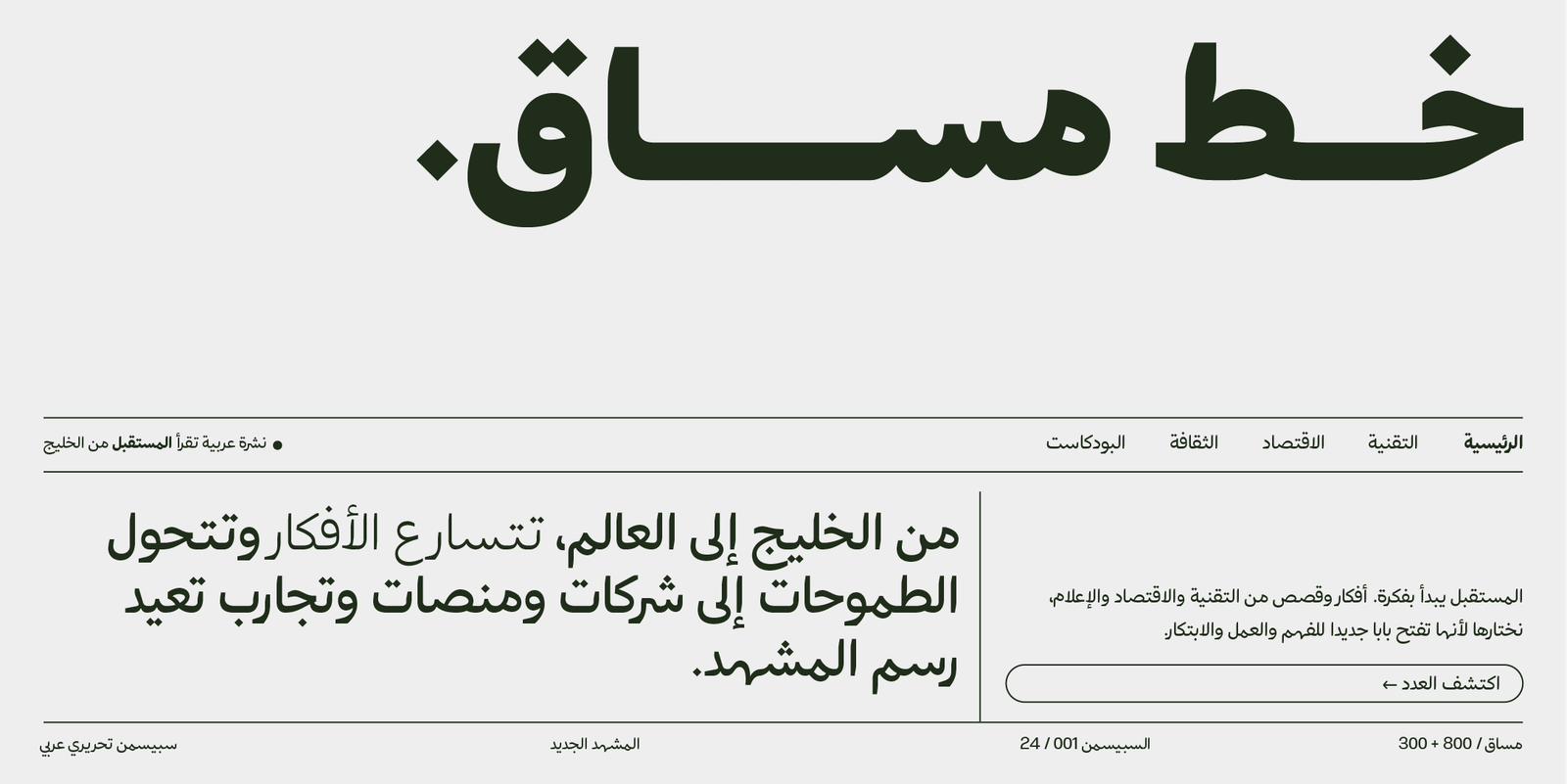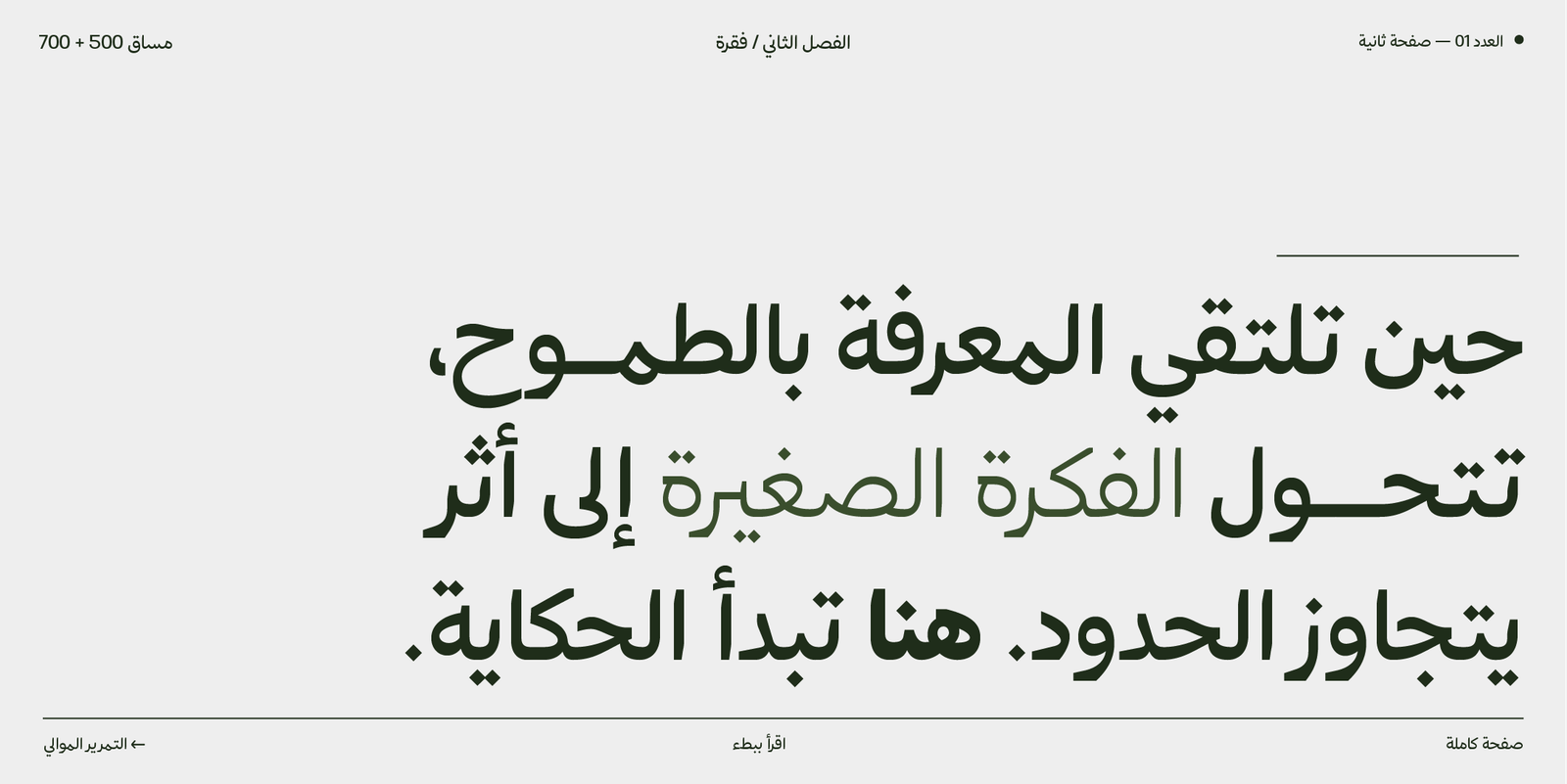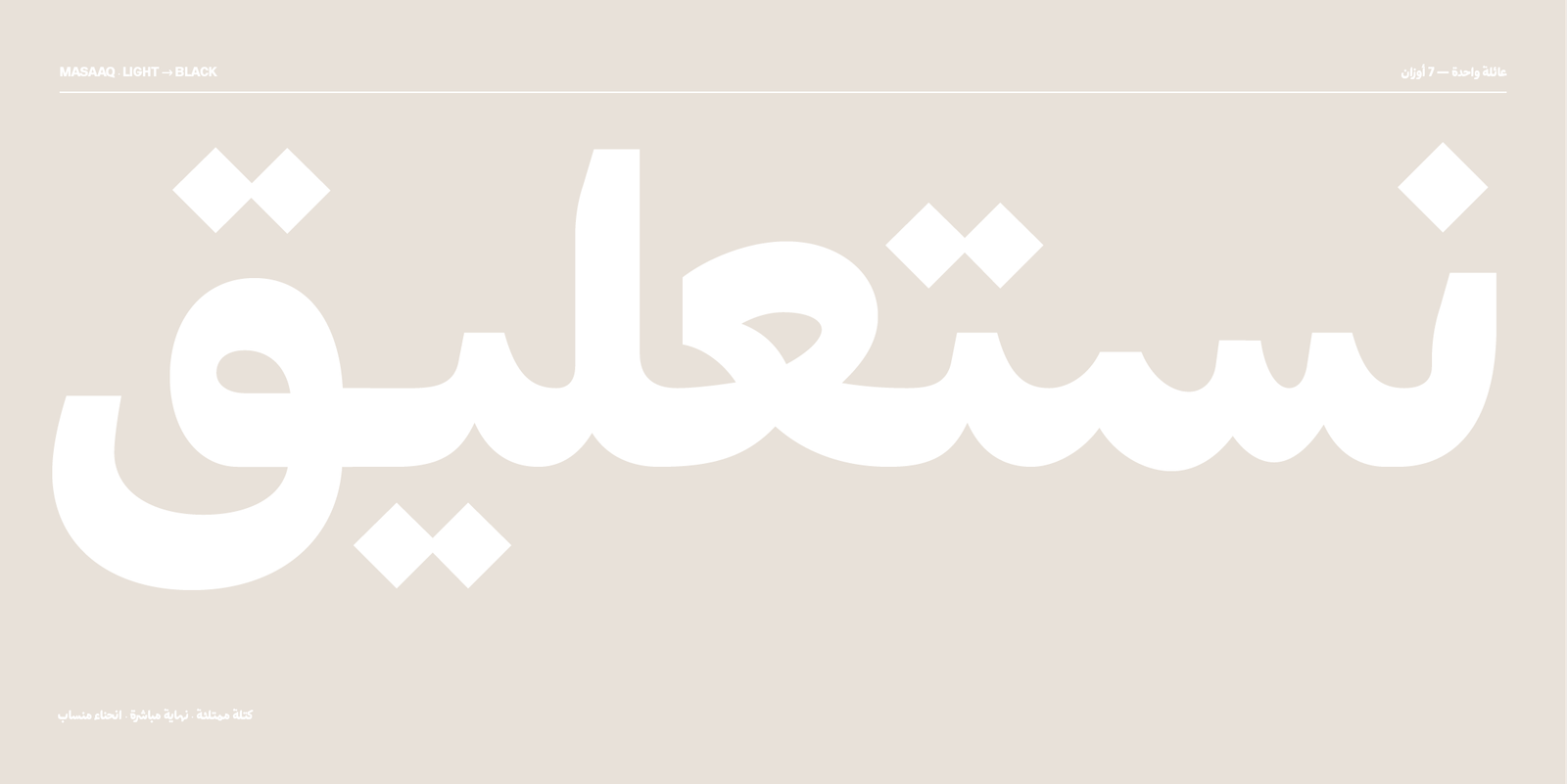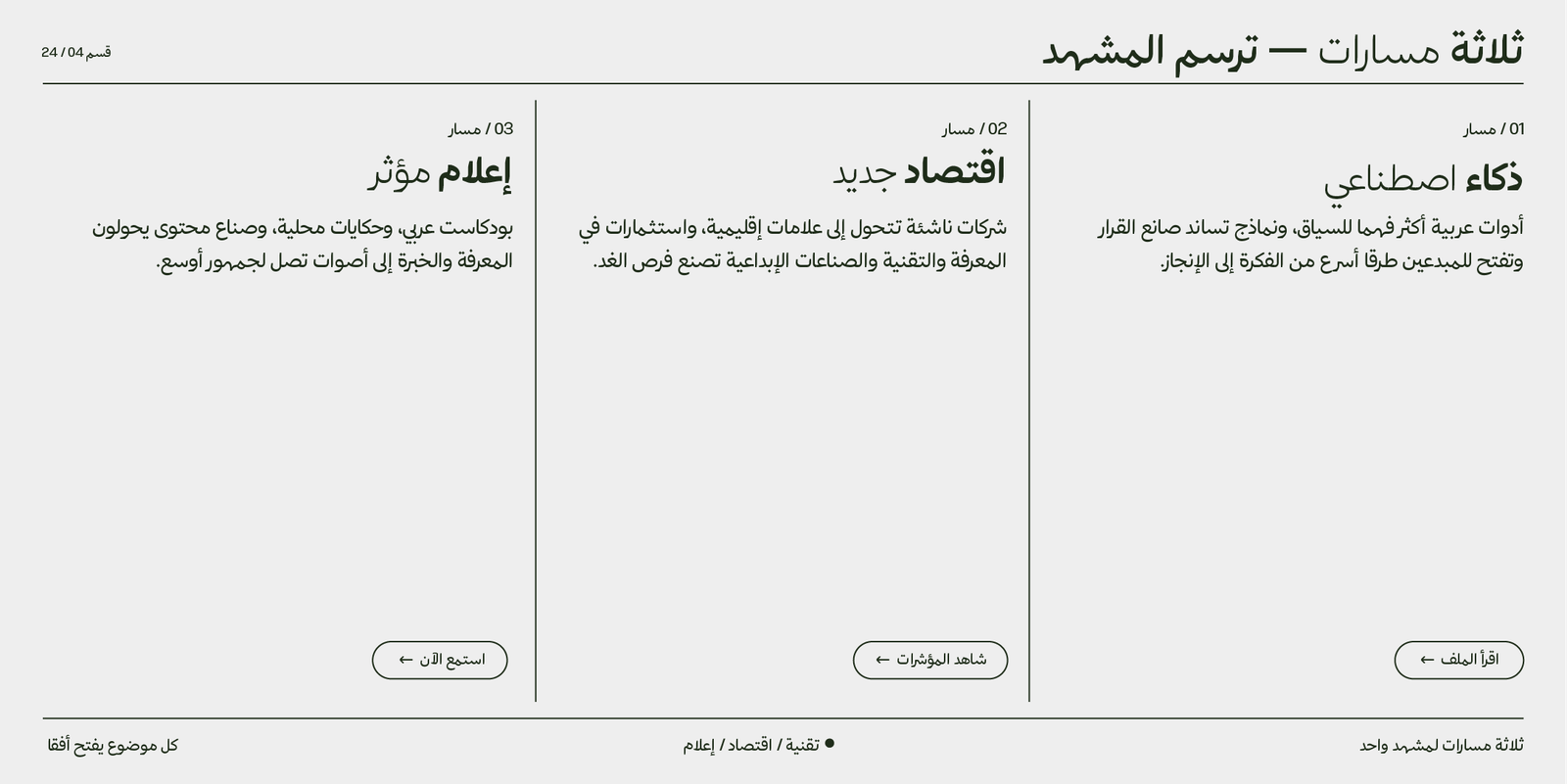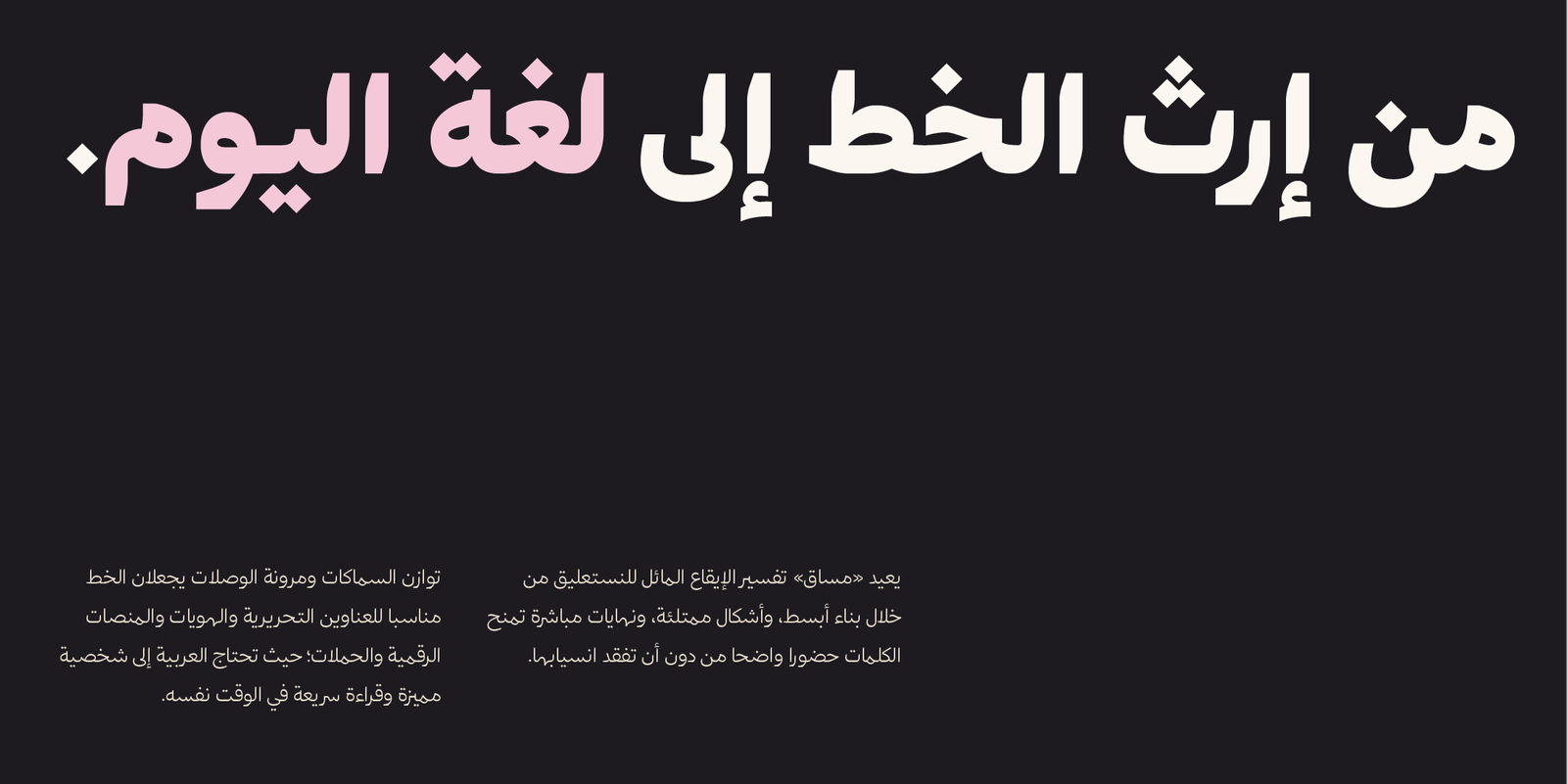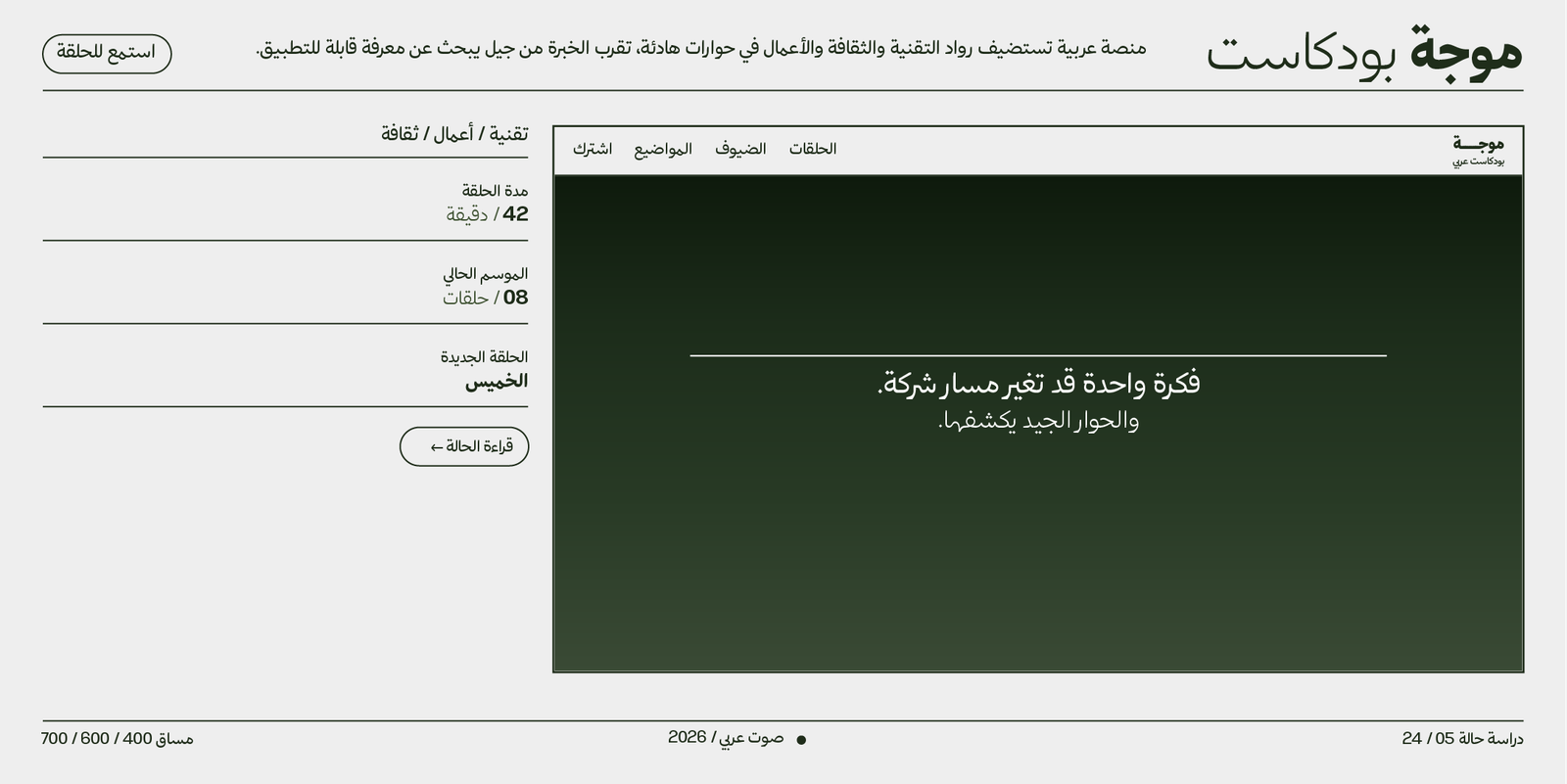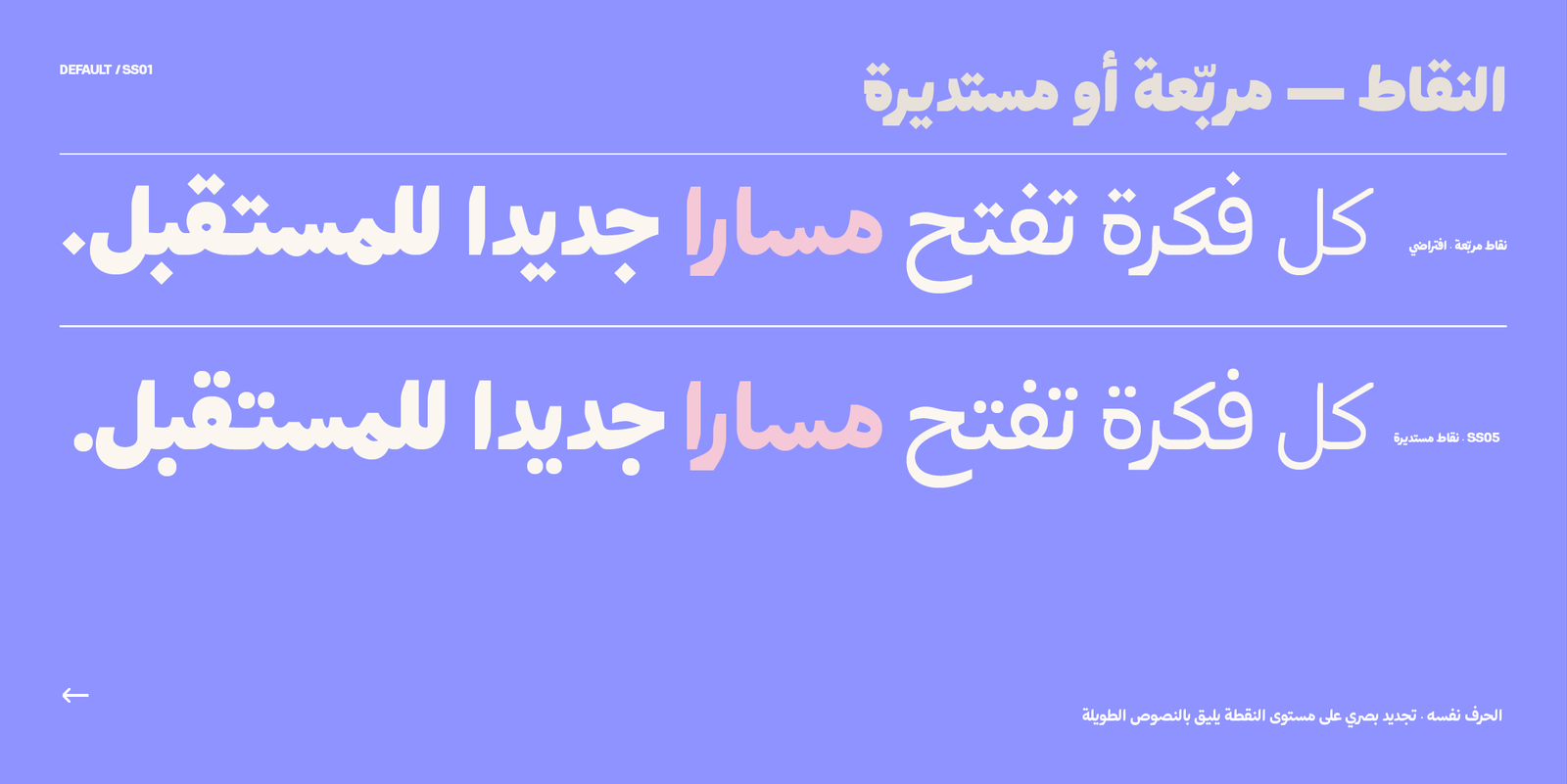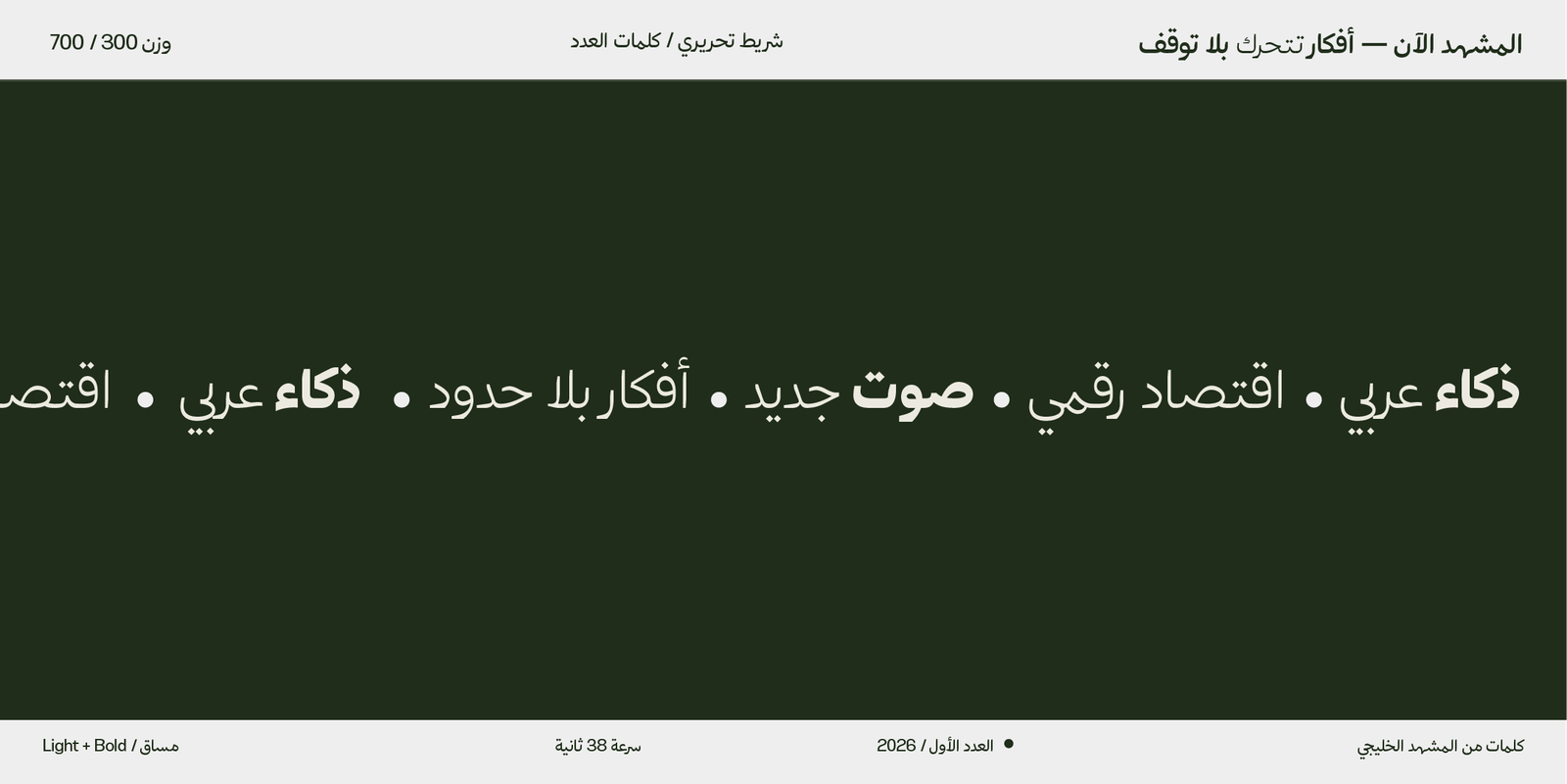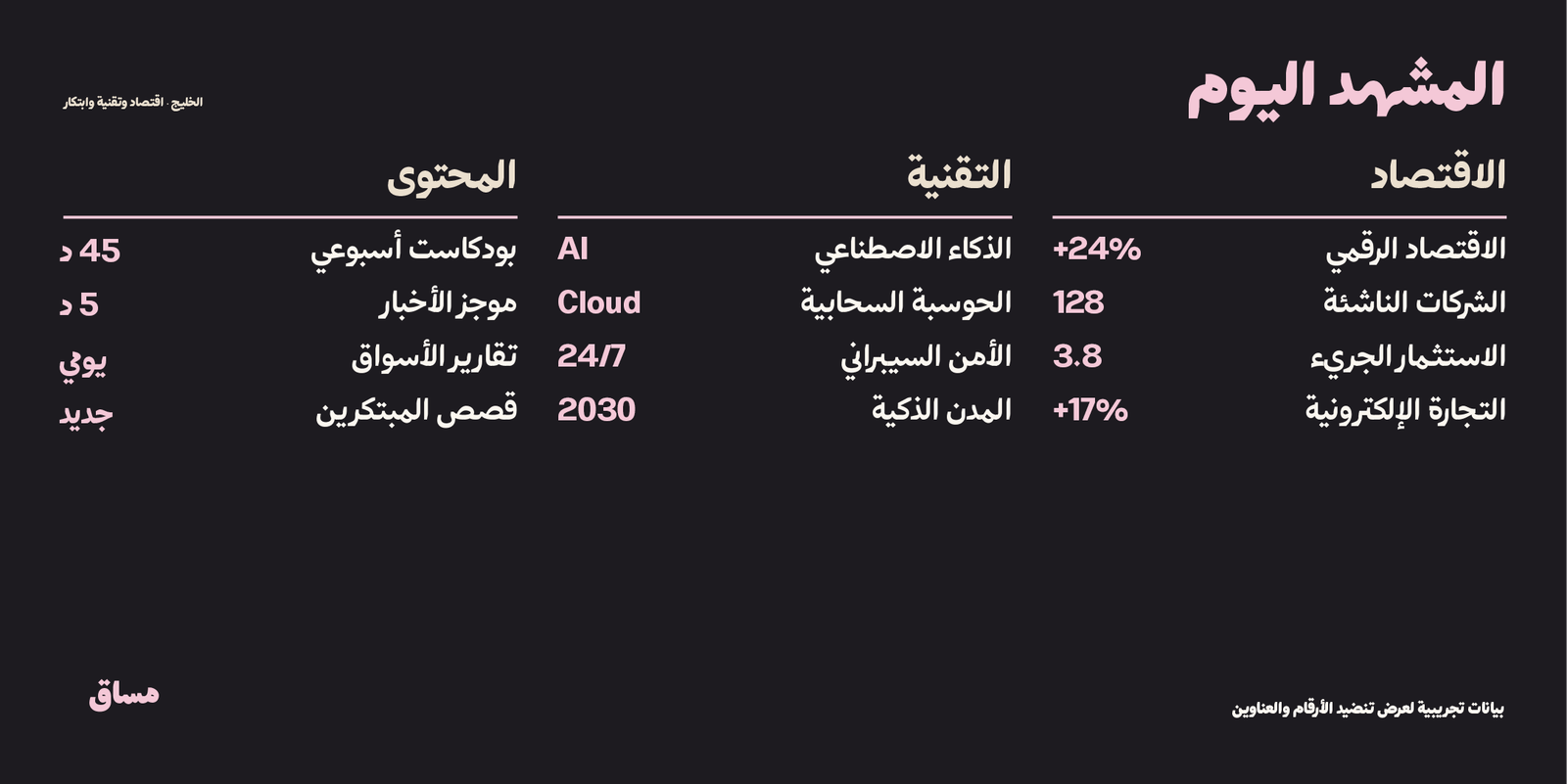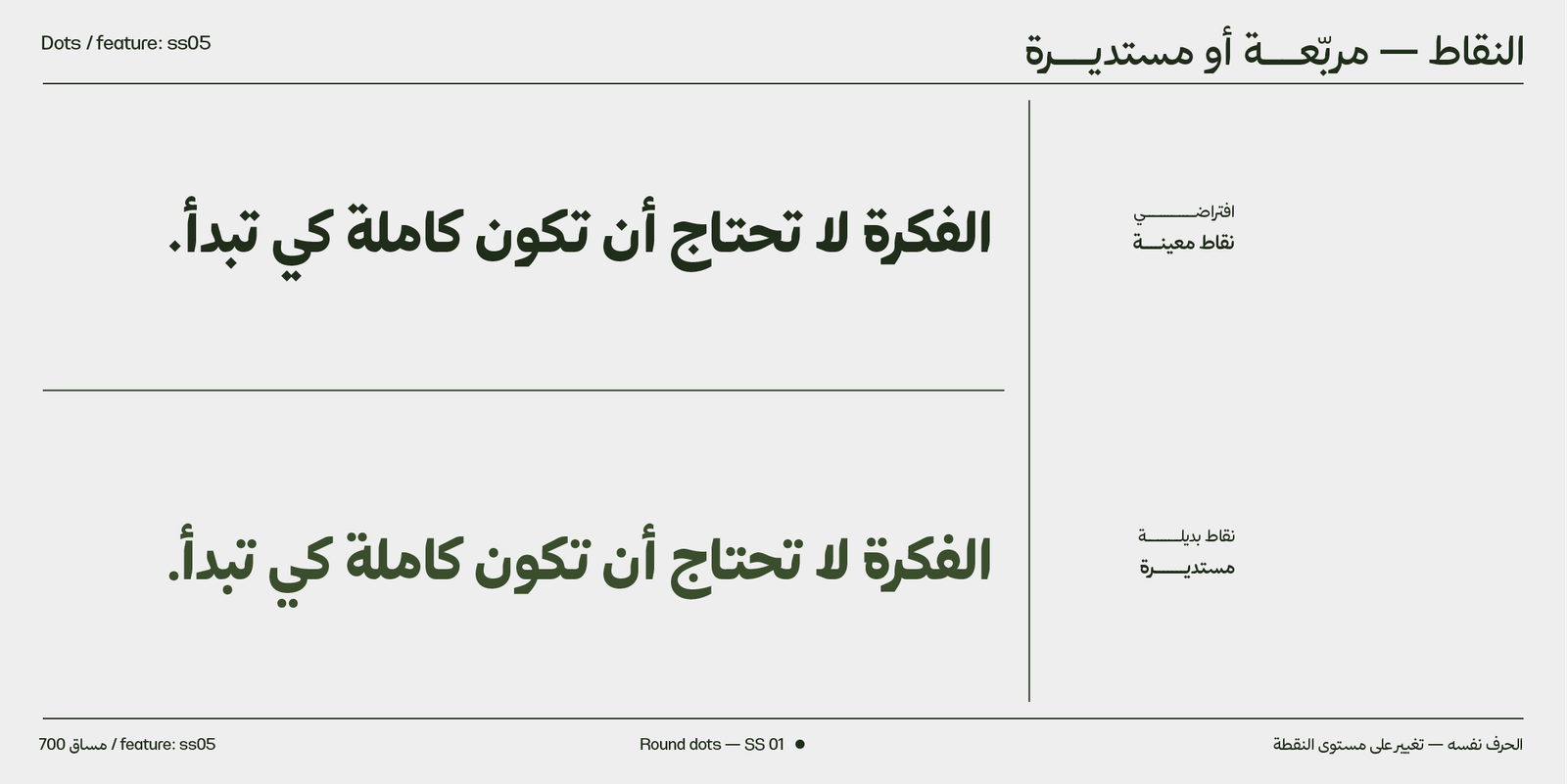
خط مساق – Masaq typeface – خط نسخ ونستعليق حديث
مساق هو إعادة تفسير معاصرة لإيقاع النستعليق، صُممت ببنية أكثر بساطة ووضوحًا، بعيدًا عن التفاصيل الخطية التقليدية.
يحتفظ الخط بانسياب الوصلات والامتدادات الأفقية المميزة للنستعليق، لكنه يعيد بناءها بأشكال ممتلئة، ونهايات مباشرة، وسماكات أكثر تجانسًا؛ ليقدّم شخصية عربية معاصرة تجمع بين مرونة الخطوط الخطية ووضوح الخطوط السانز.
النتيجة خط جريء من دون صخب، بسيط من دون أن يفقد شخصيته، وحاضر بصريًا من دون الاعتماد على الزخرفة.
مميزات خط مساق:
يتضمن الخط العديد من مزايا OpenType التي تضفي عليه مرونة وتنوعًا في الاستخدام، مثل:
- محورا استطالة في النسخة المتغيّرة يمدّان وصلات الكلمة تدريجيًا للعناوين الممتدة.
- أحرف مرسلة (تُفعَّل بإضافة “ءء” بعد الحرف)
- حرف ياء بنزول أقل: يقلل من نزول السطر، مما يعزز من انتظام النصوص.
- أحرف المركبة: تسهم في تحسين المظهر العام للنص وتزيد من سلاسته.
- نقاط بديلة
- يدعم رمز الريال السعودي، ويمكن تفعيله بإضافة حرف “ء” بعد كتابة كلمة “ريال”